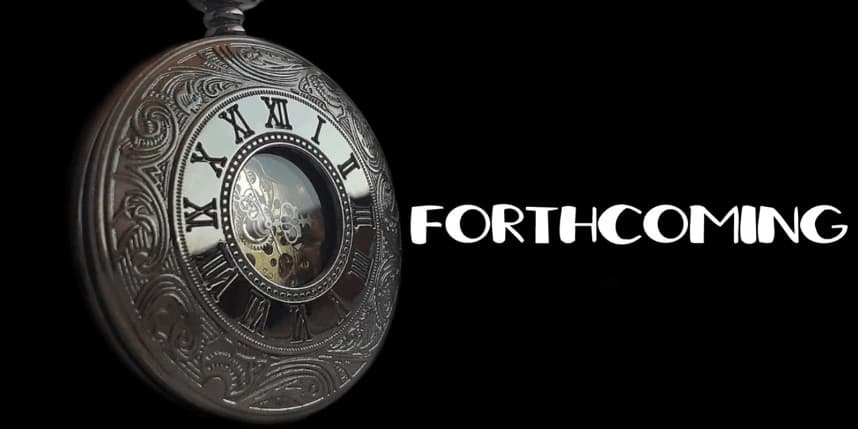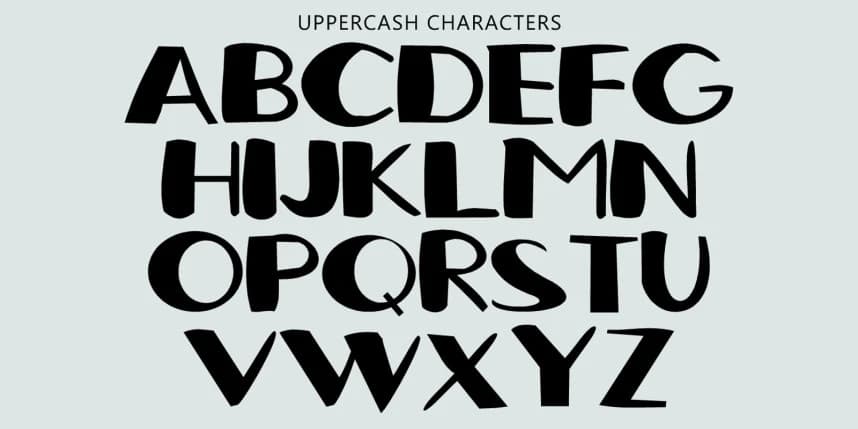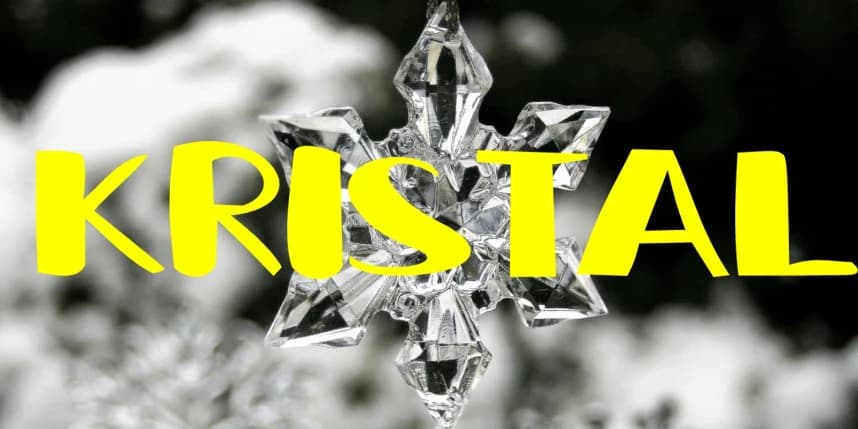
Kispray Görüntü Yazı Tipi
Kispray Display Font zarif ve karakter dolu bir gösteri yazı tipidir. Parfüm spreyinin yumuşak, ferahlatıcı etkisinden esinlenmiştir. Yumuşak ama sağlam harf biçimlerine sahip olan Kispray, kadınsı, temiz ve modern bir hava getirir—güzellik ürünleri markalaşması için mükemmel.
Kispray Display Font, zarif ve karakter dolu bir gösterim yazı tipidir; parfümün yumuşak, ferahlatıcı spreyinden ilham alınmıştır. Yumuşak ancak sağlam harf biçimlerine sahip olan Kispray, kadınsı, temiz ve modern bir his sunar—güzellik ürünleri markalaşması için mükemmel.